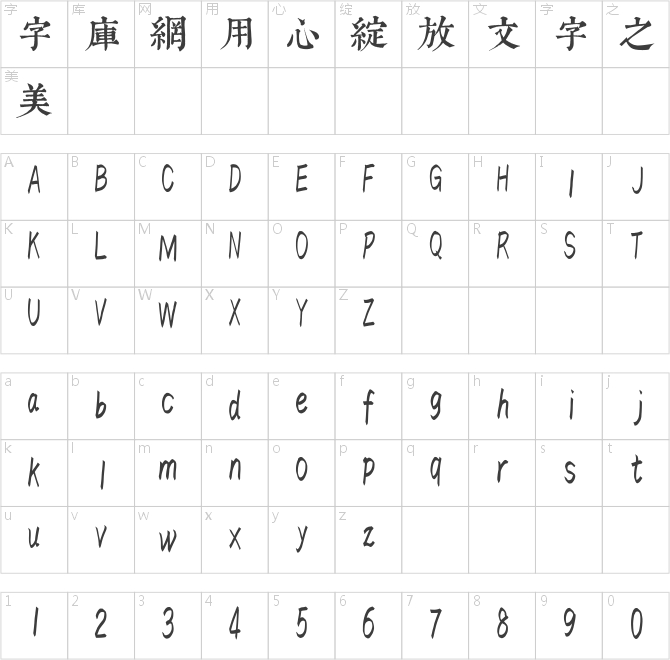
汉标康熙字典内府繁
作品的主要特征:字体版刻清晰,行格疏朗,古朴清新,雕刻刀法精湛;
作品的主要特点:最大化的保留古籍刻本字体原貌,对印制不清的字体进行了修复还原,字体边界清晰,线条流畅,大小均等。
选用清康熙五十五年(1716)武英殿刻本,又称内府刻本,康熙内府刻本多用于内廷赏赐之用,民间流传较少。该刻本为初印本,初刻初印,字典墨色浓郁,字迹秀美、雕刻刀法精湛、将原书以600dpi进行扫描并进行抠字,将原书中的文字分别提取出来,进行一些修缮后转 成矢量轮廓,并非如一般字体设计那样手动绘制矢量曲线。对一些字进行了拼版,保证了古籍印刷的美观和实用性。